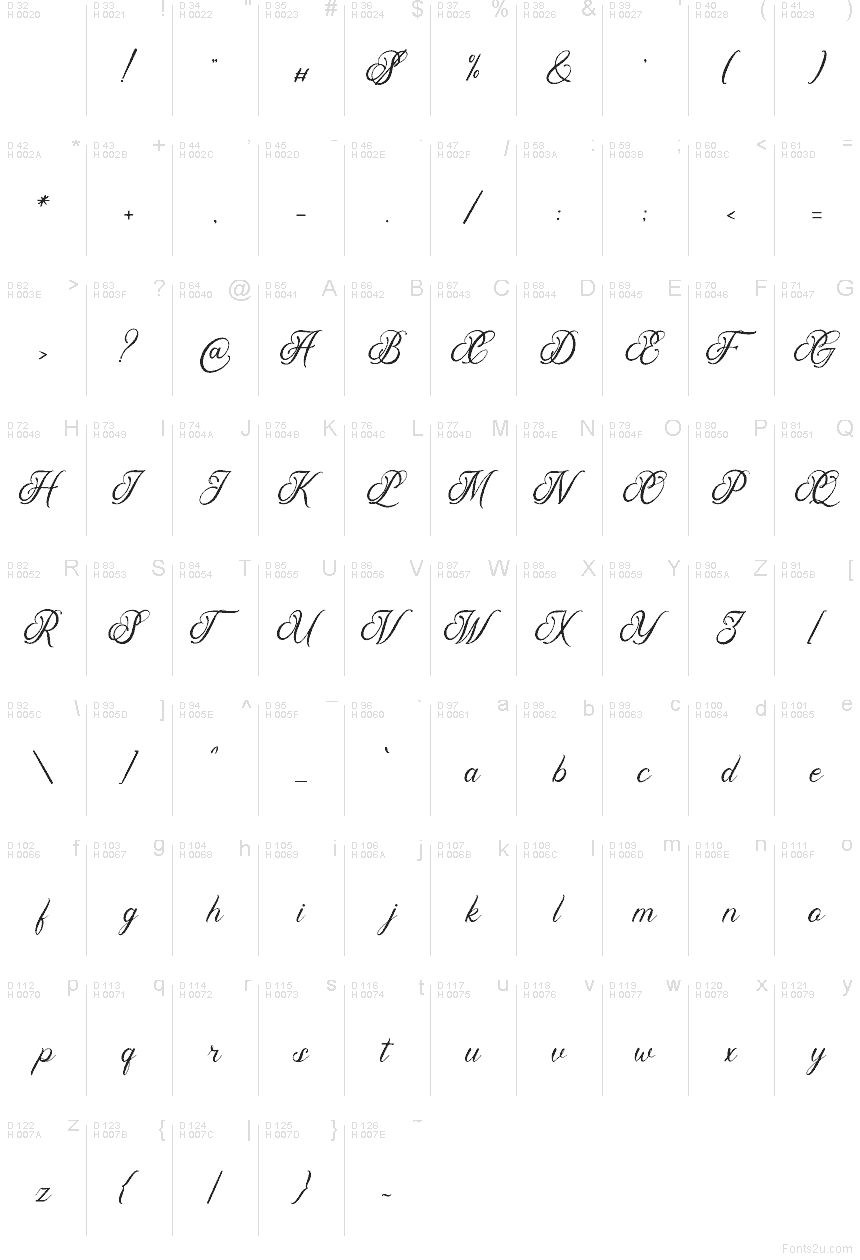
Pimfloth Bartauly od Denustudios to bezpłatny, formalny font kaligraficzny o romantycznym charakterze w stylu copperplate. Litery wyróżniają się długimi, zamaszystymi pociągnięciami początkowymi oraz wysokimi, zwężającymi się łukami, podczas gdy wielkie litery rozkwitają hojnymi pętlami, nadając całemu krojowi dostojny, niemal ceremonialny rytm.
Font ten naturalnie wpasowuje się w papeterię ślubną, branding perfum czy biżuterii, opakowania butikowe, okładki książek oraz eleganckie nagłówki w mediach społecznościowych, gdzie rozciągnięte pociągnięcia potrafią wypełnić układ nawet przy niewielkiej ilości tekstu. Jako darmowy font, sprawdza się szczególnie dobrze przy imionach, monogramach, tytułach i wizytówkach, ponieważ ozdobne wielkie litery nadają projektowi charakteru własnoręcznego podpisu, zanim jeszcze dodasz cokolwiek innego.